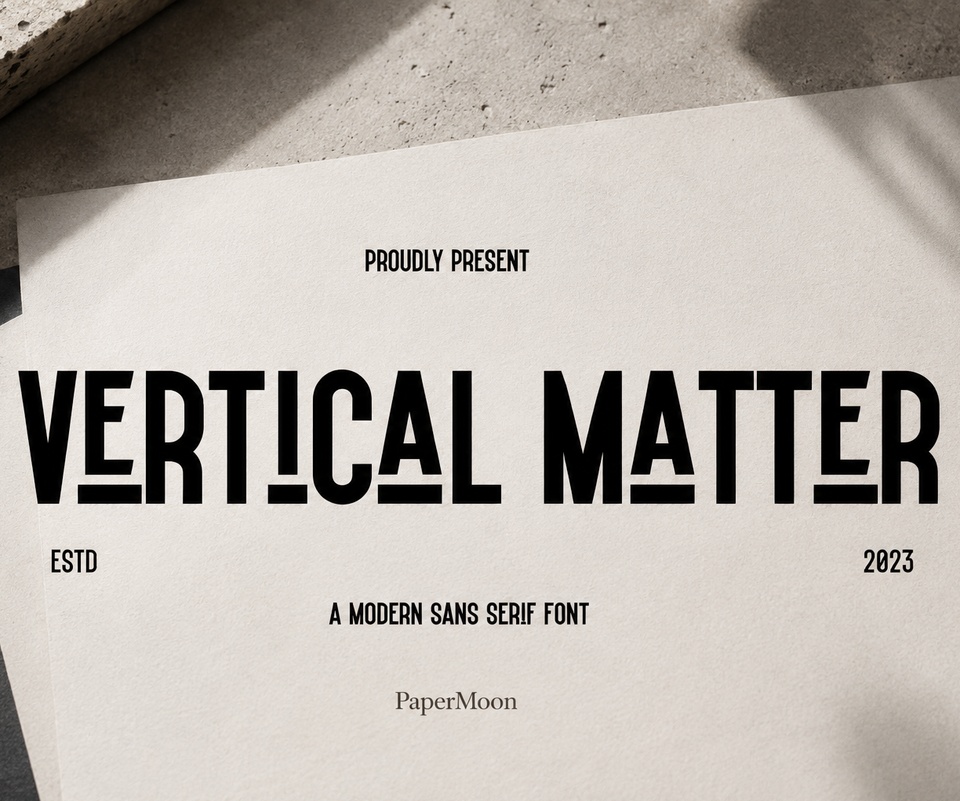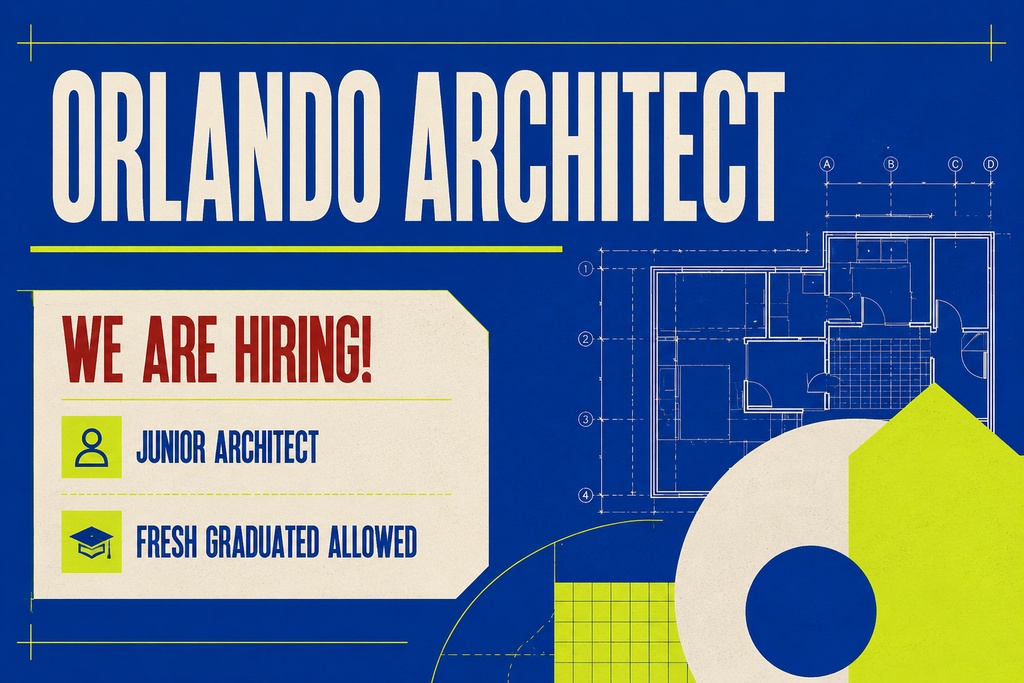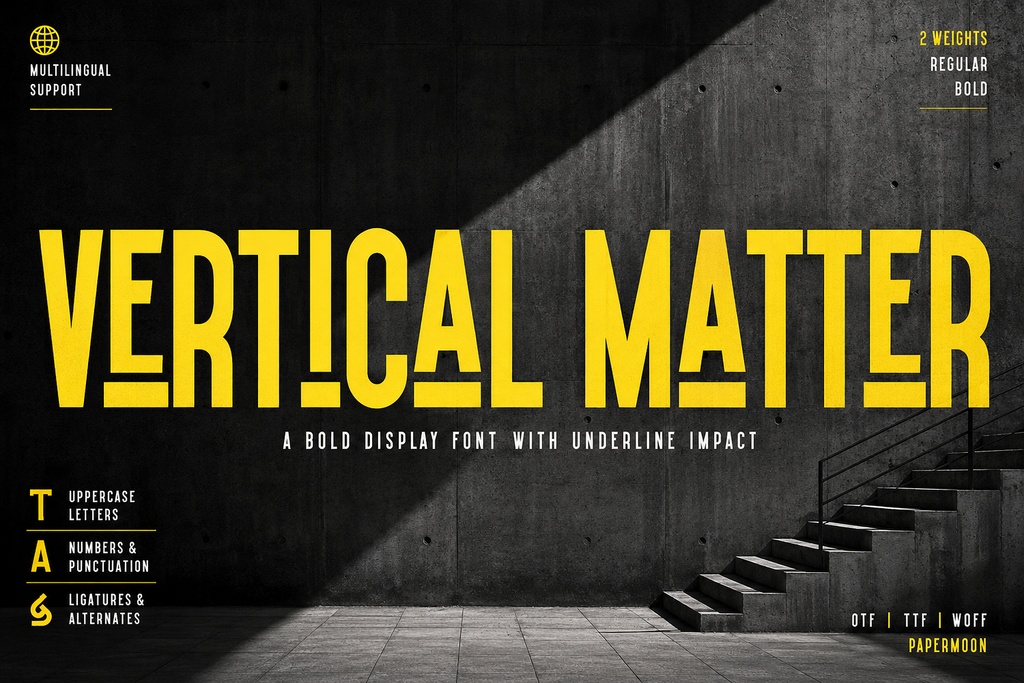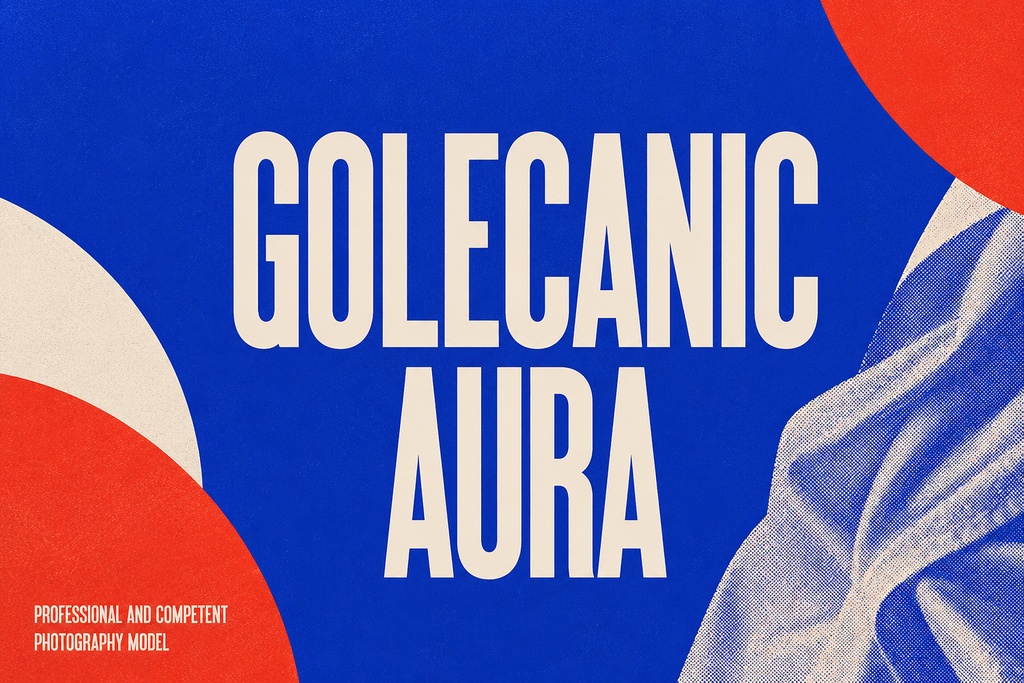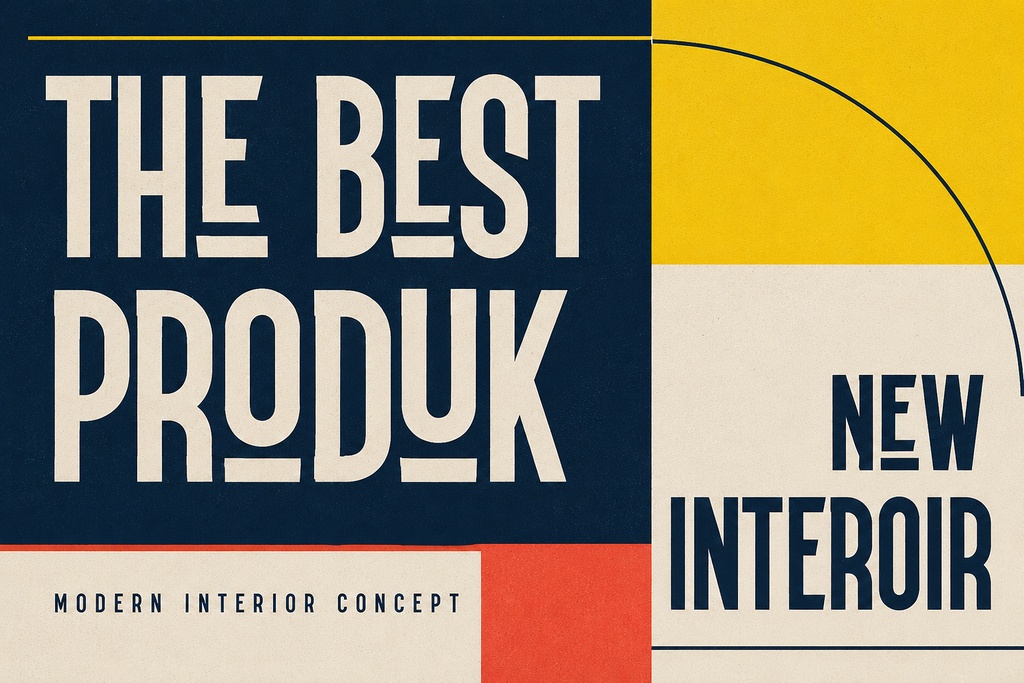
Vertical Matter — モダンでスポーティなディスプレイサンズフォント
**Vertical Matter** は、モダンでスポーティーな雰囲気を持つサンセリフ系ディスプレイフォントです。大胆なビジュアルエネルギー、クリーンなライン、シャープなコーナー、そしてアスレチックな精密さを備えています。コンパクトなディスプレイ向けデザインにより、スポーツブランド、フィットネスプロモーション、アクションポスター、スポーツウェアのグラフィック、アクティブライフスタイルのキャンペーンなどに、ダイレクトでインパクトのある表現を与えます。また、大胆な見出し、ロゴ、ラベル、パッケージ、SNS用アートワークにも、洗練されたテクノロジー感と現代的な印象を加えます。 ### 収録内容 Vertical Matter は、ディスプレイタイポグラフィ向けの **Regular スタイル1種類**で提供されます。 パッケージには以下が含まれています。 * OTF:101グリフ * TTF:102グリフ * マッピング済み文字:160文字 * Basic Latin * Latin-1の主要な句読点およびアクセント付き文字 * Latin Extendedの文字1文字 **キリル文字およびギリシャ文字には対応していません。** 制作前に、ご使用の言語で必要な文字が収録されているかをご確認ください。 ### 主な特徴 クリーンな幾何学的構造とシャープなコーナーを持つデザインにより、大きな見出しサイズでも高い視認性と力強さを維持します。 GSUBやGPOSの機能テーブルを使用しない、シンプルなディスプレイサンセリフフォントとして設計されています。代替グリフ、リガチャ、カーニング機能は含まれておらず、これらの機能も提供されていません。 対応するデザインソフトにフォントを直接設定することで、ポスター、チームグラフィック、キャンペーン見出し、ブランドロゴなどをコントロールしやすく制作できます。 ### 用途 このアスレチックなフォントは、以下のようなデザインにおすすめです。 * ジム・フィットネスプロモーション * スポーツチームのブランディング * イベントポスター * レース・スポーツグラフィック * アクションポスター * アパレル・スポーツウェア * スニーカーキャンペーン * 商品ラベル・パッケージ * 大胆な広告見出し * テクノロジーブランディング * アクティブライフスタイルコンテンツ * YouTubeサムネイル * SNS用アートワーク * エディトリアル向けディスプレイテキスト * エネルギッシュなロゴデザイン 大きな文字に強いコントラストやゆったりとした文字間隔、または大胆なトリミング構成を組み合わせることで、ダイナミックなスポーツブランディングを演出できます。 ### 対応形式・互換性 ダウンロードには以下の **Vertical Matter Regular** ファイルが含まれています。 * OTF * TTF * WOFF * WOFF2 OTFおよびTTFは、以下を含む対応ソフトウェアで使用できます。 **Adobe Photoshop、Illustrator、InDesign、Microsoft Word、Canva、Procreate、Figma、Affinityシリーズ、Cricut Design Space、Silhouette Studio** など、インストールしたフォントに対応する各種ソフトウェア。 Webプロジェクトでは、適切なCSSの **@font-face** 設定を使用してWOFFまたはWOFF2を利用できます。ご自身の制作環境に必要な形式のみをインストールしてください。 ### ライセンス こちらは **PaperMoon 2026 Commercial Pro Package** です。 Cubebrush Commercial Licenseは、ライセンス規約の範囲内で、商用クライアントワーク、ブランディング、マーケティング、デジタルデザイン、物理製品、販売用製品などの商業目的で使用できます。 フォントファイルそのものを単体のアセットとして、再配布・再販売・共有することは禁止されています。 現在のアップローダーでBasic Licenseが選択できる場合、Basic Licenseは個人利用および非商用プロジェクトのみに使用してください。 **Vertical Matter** で、次の見出し、スポーツウェアグラフィック、フィットネスキャンペーン、またはアクティブなブランドアイデンティティに、正確で力強いアスレチックなエネルギーを加えてみましょう。